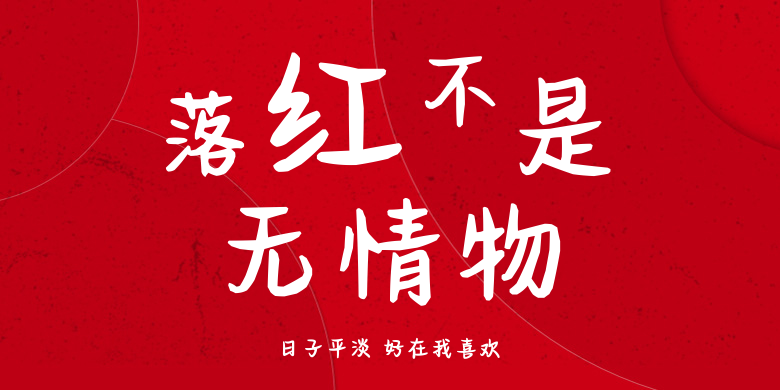
日子平淡 好在我喜欢
日子平淡 好在我喜欢,这款字体结构工整、笔画清晰,兼顾美观与易读性,适用于标题、正文、海报、包装、LOGO 等多种场景。字形优雅稳定,风格百搭耐看,适配日常排版与创意设计,让文字呈现更舒适、更具质感。日子平淡 好在我喜欢一笔一画,皆是细节,以均衡的比例、流畅的线条打造舒适视觉体验,字形端正大气,风格简约现代。无论是商业设计、品牌宣传还是日常排版,都能轻松驾驭,让文字更有格调与力量。日子平淡 好在我喜欢字体下载。